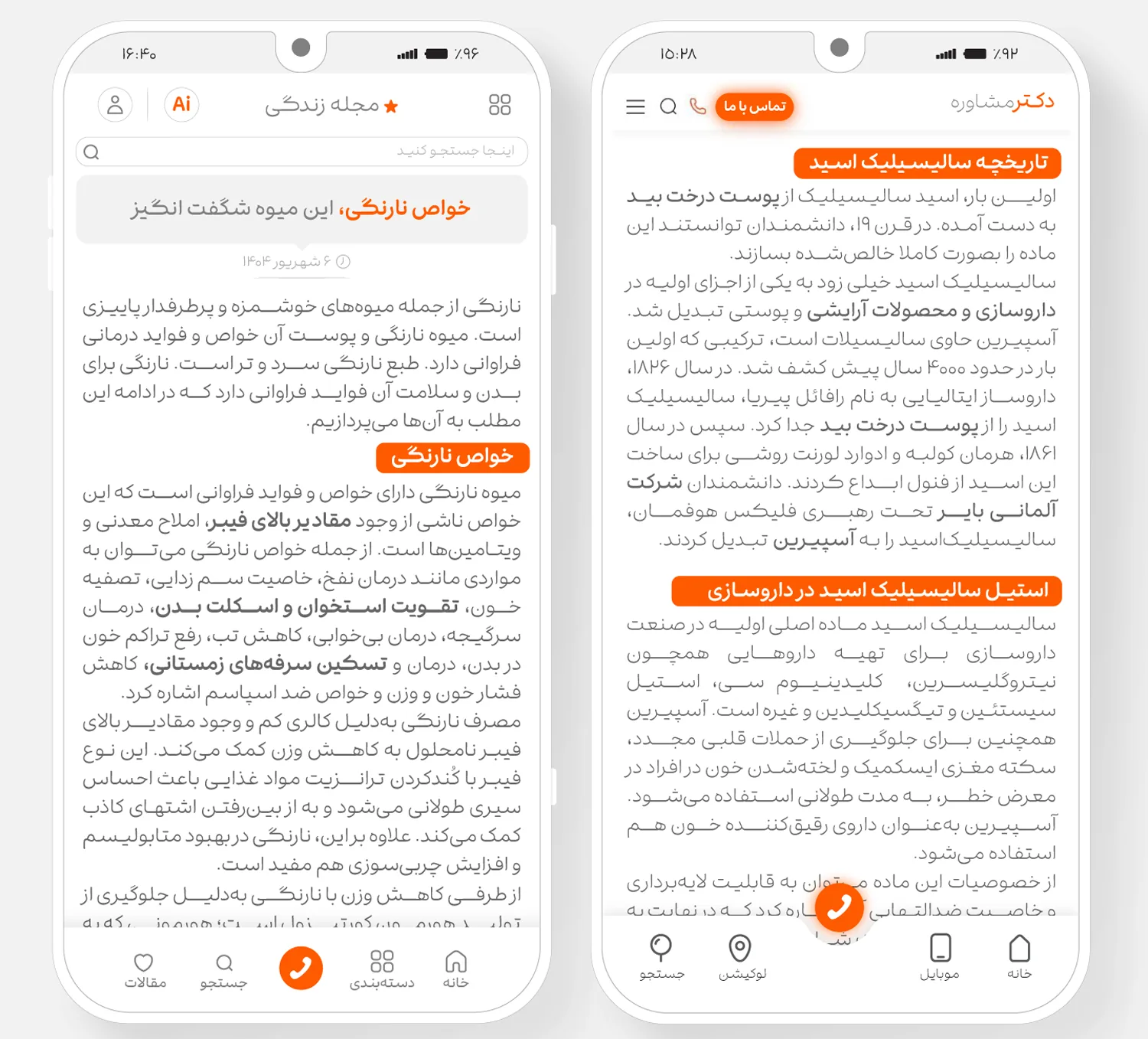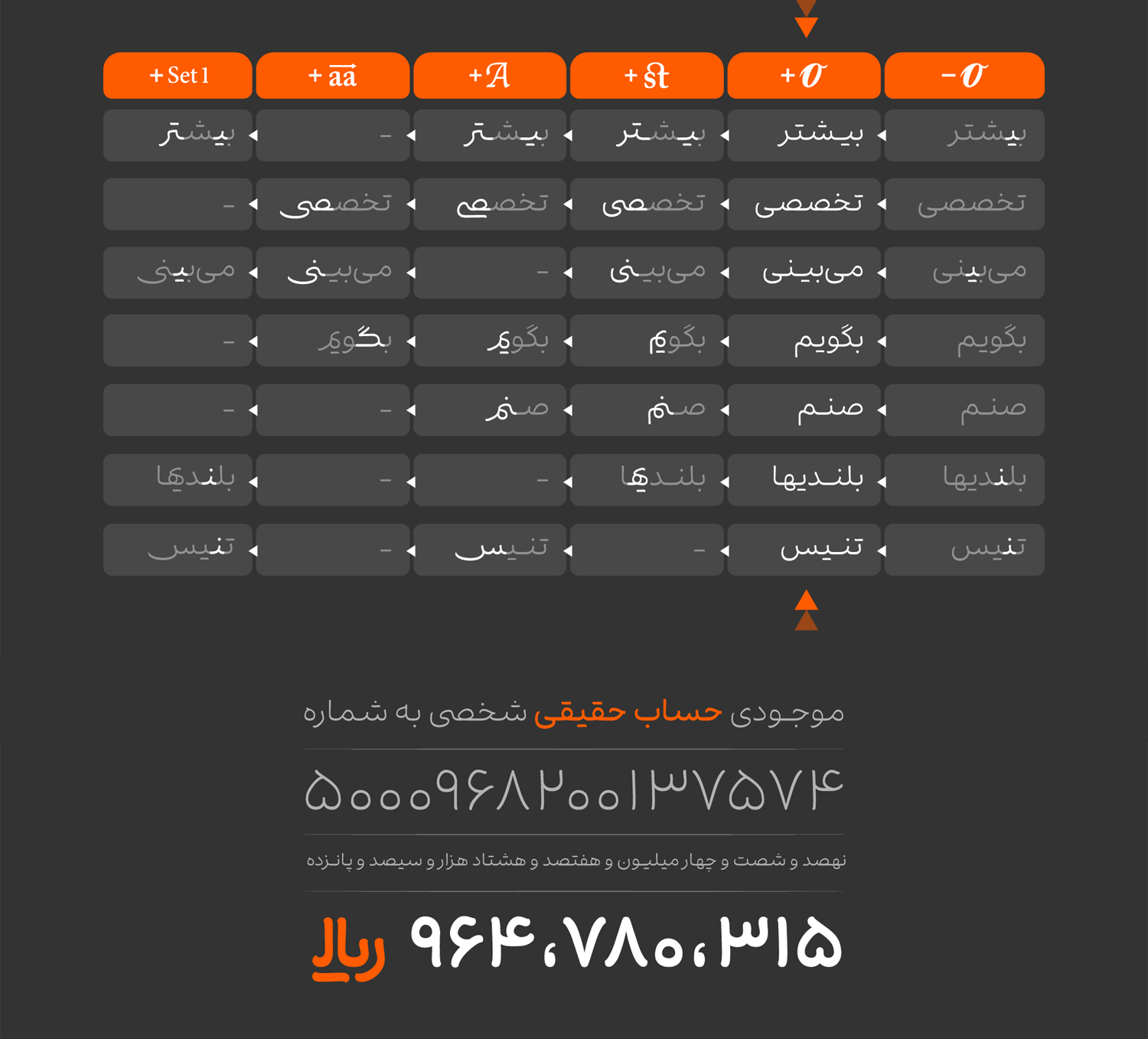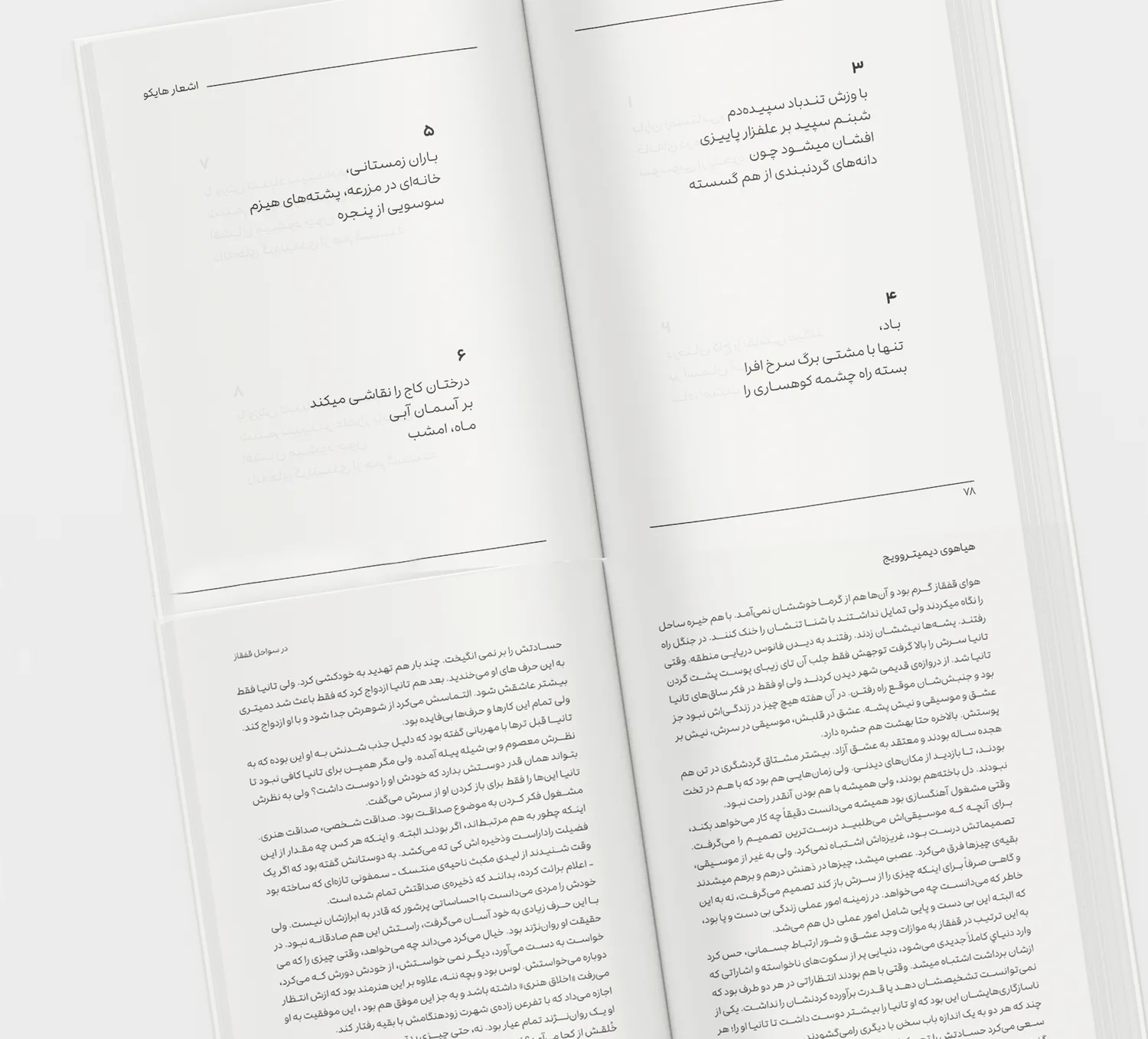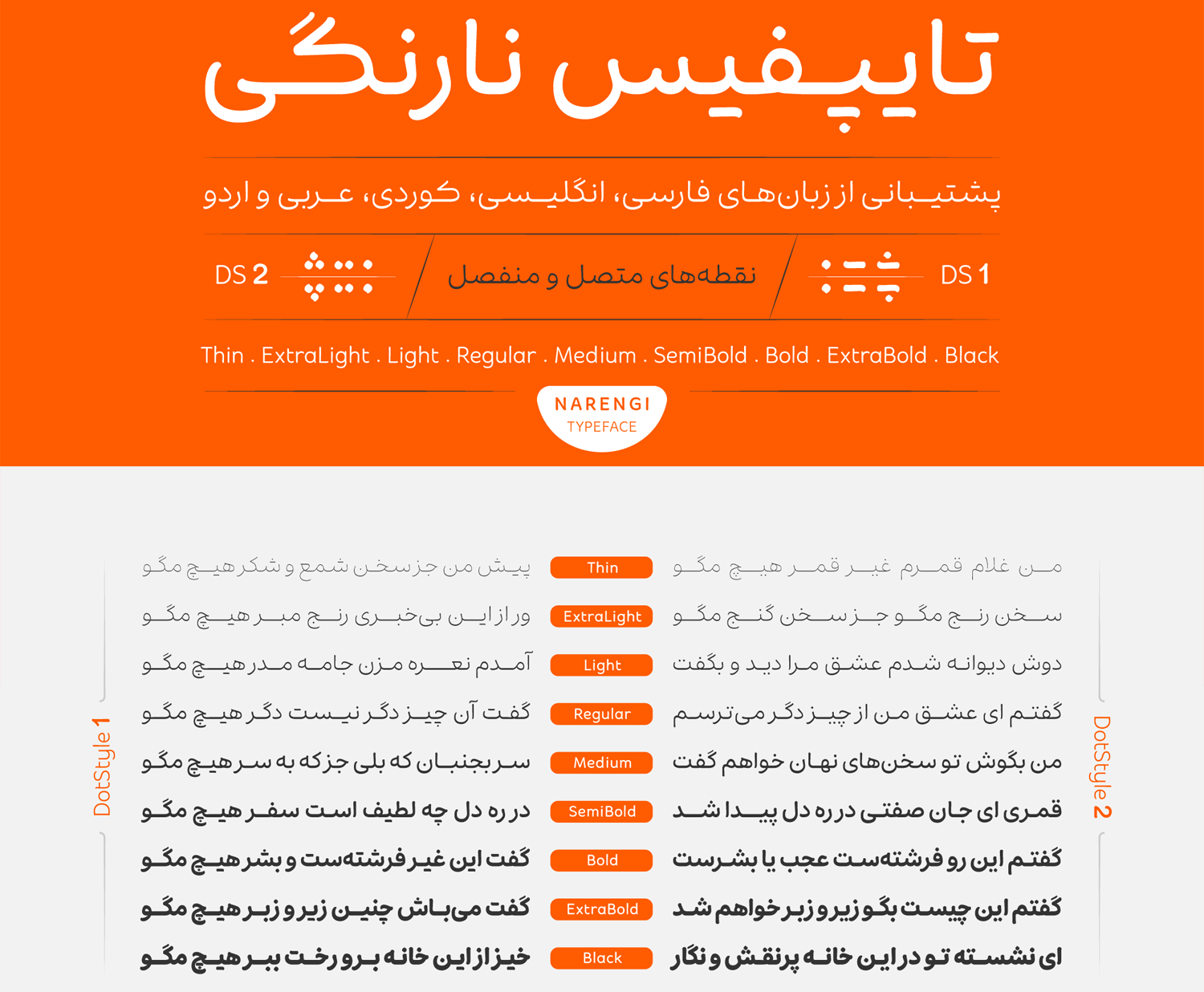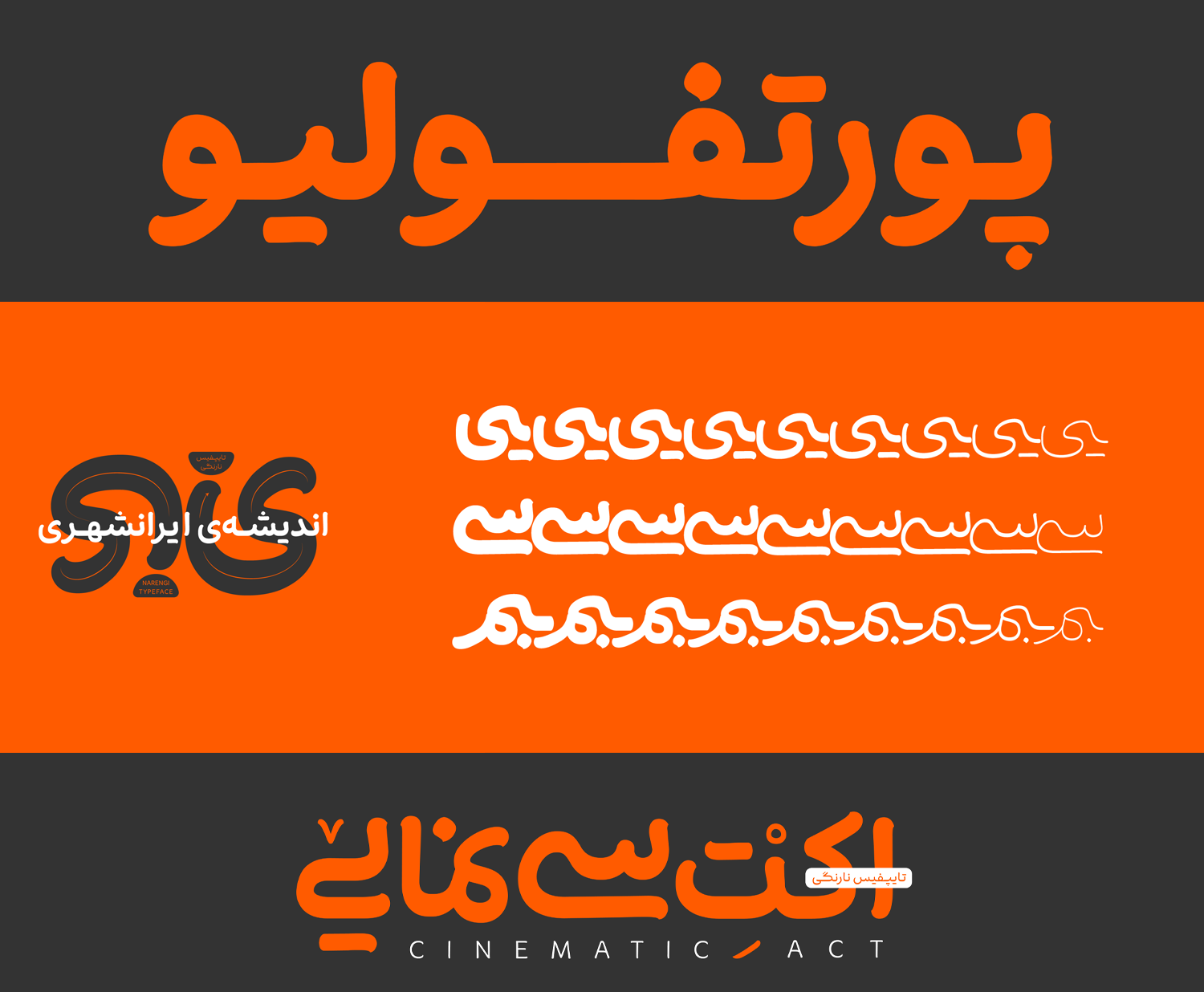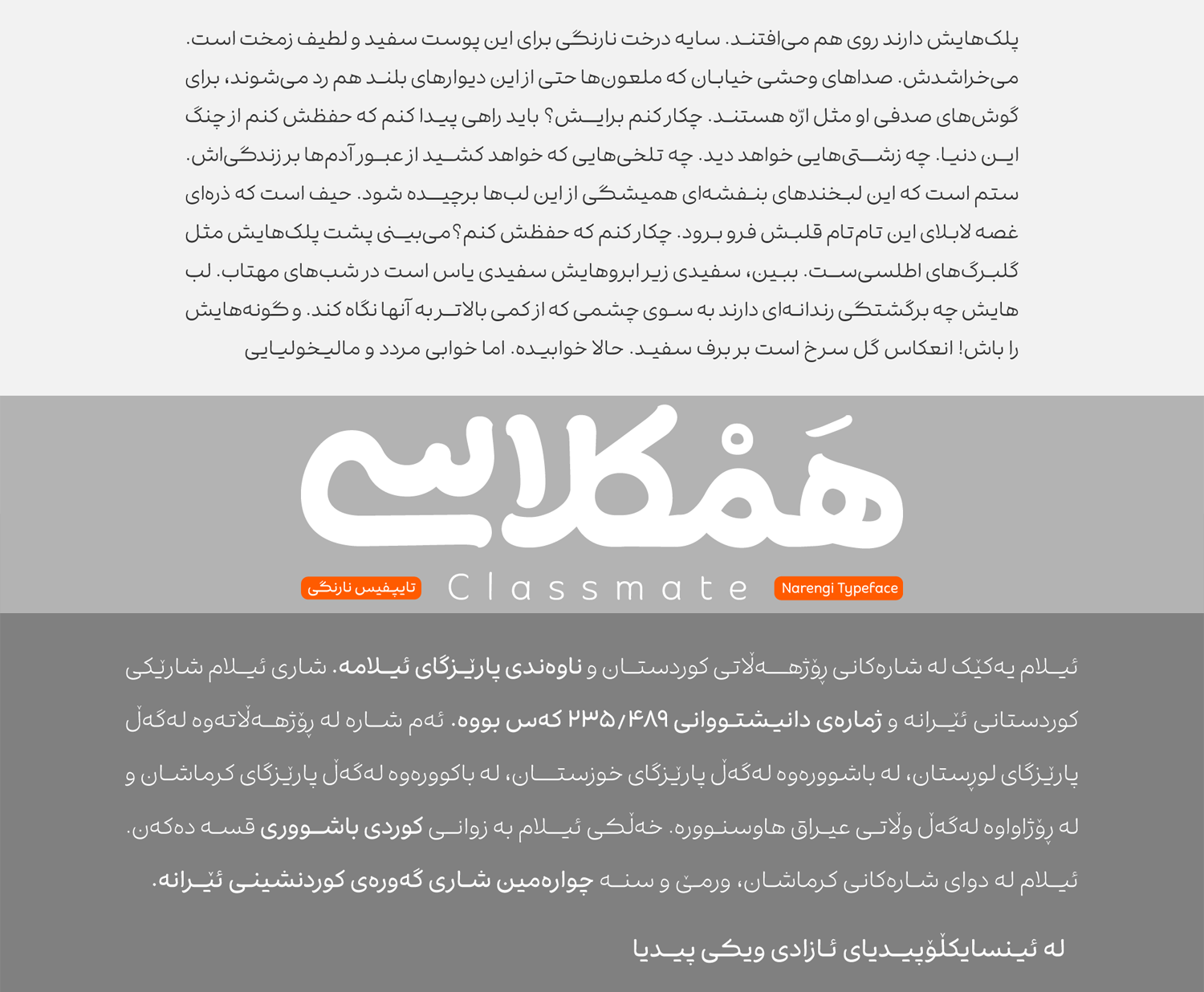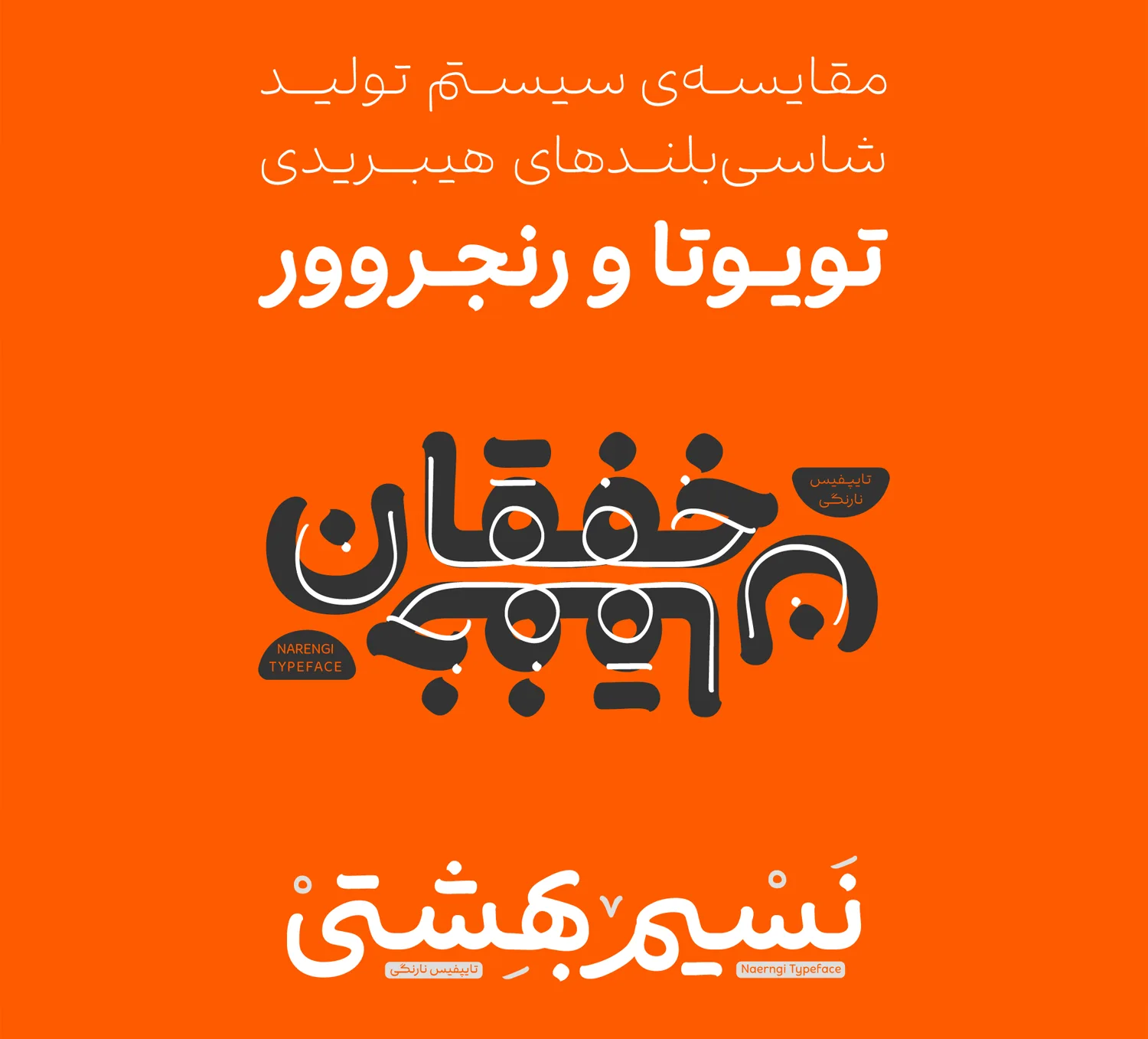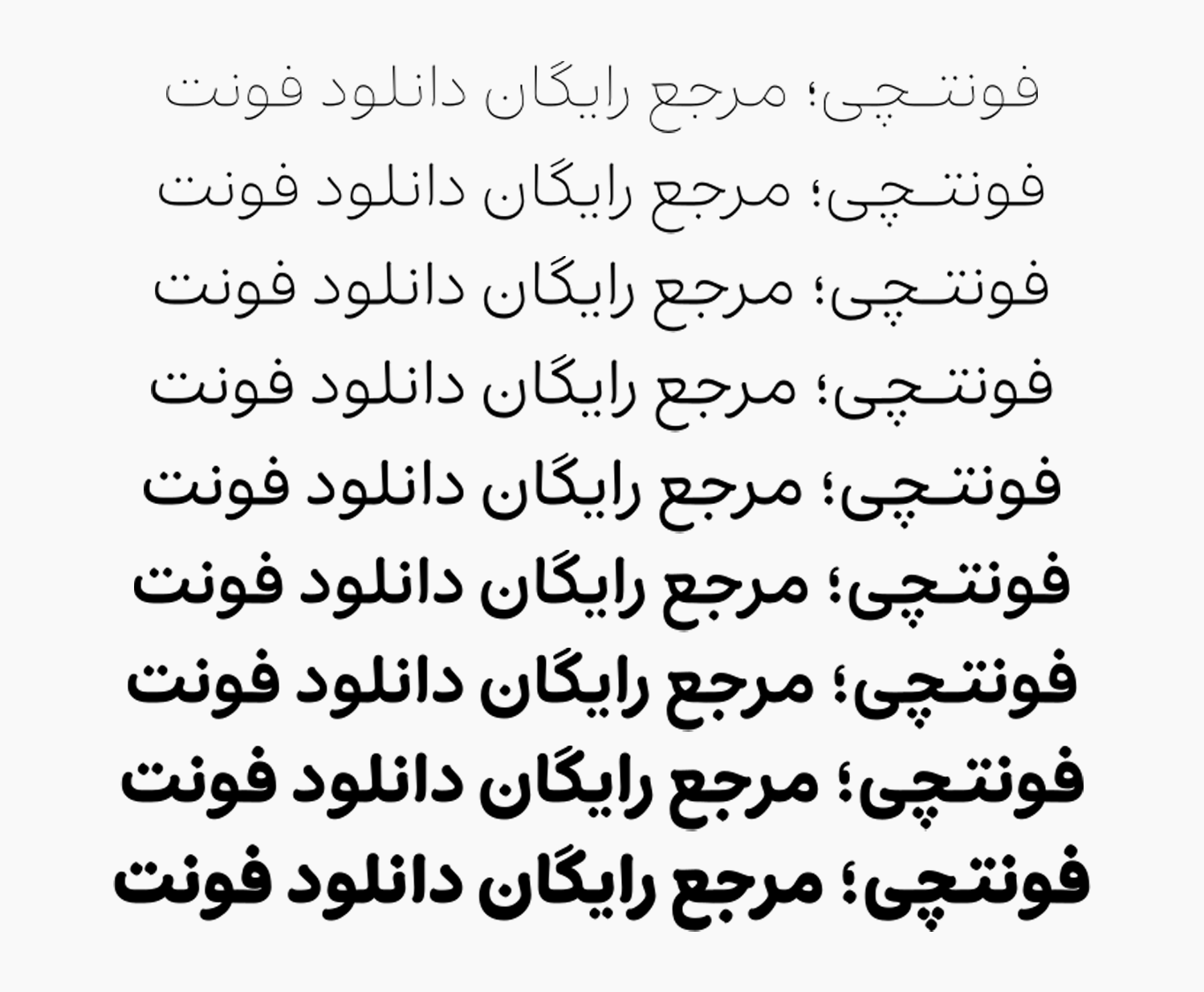
فونت نارنگی (Narengi)
طراح کریم شاهین
فونت نارنگی (به انگلیسی: Narengi) از سری فونت جدید فارسی با ساختاری دست‌نویس است که با ۹ وزن متنوع نازک تا سیاه ارائه شده است. این فونت که از نسخه متغیر وریبل با قابلیت استفاده از دو نوع سبک نقطه‌گذاری پشتیبانی می‌کند، گزینه‌ای عالی برای تبلیغات، عناوین و طراحی رابط کاربری در اپلیکیشن و وب‌سایت است.
شاهین کریم با شرکت در دومین همایش هفته تایپ تهران با نام «فونت براش» عنوان فونت برگزیده را ازآن خود کرد که در نهایت با کار بیشتر روی این فونت و تغییرات متعدد، با نام فونت نارنگی عرضه عمومی شد.
در طراحی این فونت از حرکات طبیعی و پویای قلم‌مو الهام گرفته شده تا ساختاری دست‌نویس و دوستانه را در فونت القا کند. منحنی سیال در حروف صمیمیت را افزایش داده است، چشمی حروف با ساختاری نسبتا بزرگ در برخی حروف، نگاه را از مخاطب می‌دزدند و گوشه‌هایی که به شکلی خاص تقریبا نازک و تغییر حالت داده شده، حس قلم‌مویی را منتقل می‌کنند.
این فونت در نگاه اول شاید کمی هندسی به‌نظر برسد، اما تلاش شده تا ساختار سیال به قلمو داده شود تا با انتقال حرکتی پویا، نرم و دوستانه، ساختاری دست‌نویس را از چنین سبکی خارج کند که موفق هم بوده است.
فونت نارنگی محدود به زبان فارسی نیست؛ عربی، کوردی، انگلیسی و اردو دیگر زبان‌های پشتیبانی شده در این فونت ۹ وزنی هستند. در بخش اعداد شاهد ارائه دو نسخه متفاوت از فایل فونت‌ها هستیم. گروه اول فایل‌های عادی که هر ۳ نسخه اعداد عربی، انگلیسی و فارسی را در خود دارند. اما نسخه مخصوص اعداد فارسی هک شده که مناسب استفاده در برنامه‌نویسی و ساخت اپلیکیشن هستند، الزاما اعداد عربی و انگلیسی هم در آنها به شکل فارسی تایپ می‌شود.
به‌منظور نمایشی کردن فونت نارنگی دو متغیر در نسخه وریبل فونت درنظر گرفته شده که می‌توانید از دو سبک نقطه‌گذاری متصل و منفصل استفاده کنید. در هر دو سبک شاهد آن گوشه‌های تغییر یافته و نسبتا نازک‌تر قلمو در بخش نقاط هستیم.
در برخی حروف و ترکیبات نارنگی شاهد استفاده از کشیدگی‌های خاصی هستیم. برای مثال حروف «ک، گ» که علاوه برکشیدگی، خط بالای آنها نیز شکل متفاوتی از ساختار حروف اصلی را دارند. این کشیدگی‌ها با ۳ هدف ایجاد شده‌اند:
• انعکاس ساختار آوایی زبان فارسی در ساختار بصری فونت
• الهام از کشیدگی‌های خط نستعلیق برای ایجاد ریتم در نوشتار و پرهیز از یکنواختی بصری
• ایجاد تعادل و نظم در کنار منحنی‌ها و دورهای متعددی که هم در استخوان‌بندی و هم در فرم کلی حروف وجود دارند
در وزن‌های پایین مناسب متون، این کشیدگی‌های عرضی، سکون و تعادلی بصری در برابر انحناهای زیاد حروف ایجاد می‌کند و از بهم ریختگی متن جلوگیری می‌کند. برای وزن‌های سنگین‌تر و کاربردهایی همچون تیترها و عناوین، این کشیدگی‌های عرضی کاهش یافته‌اند تا امکان نمایش کلمات درشت‌تر در فضای محدود فراهم شود.